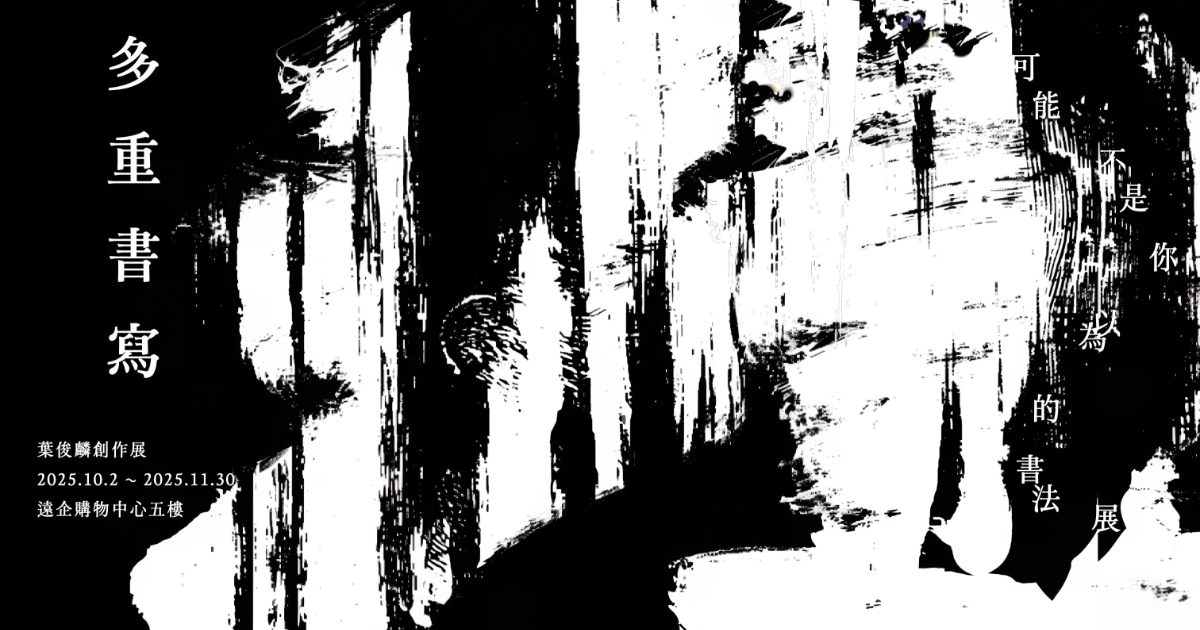
書法長久以來被視為展現個人美學與人格的藝術形式,講究基本功,要具備筆法、章法及書寫氣韻。然而隨著時代的推進,文字的使用情境與意義不斷轉變,當代書法該如何回應這樣的語境?這正是這次展覽企圖探索的問題。
「多重書寫」不僅意味著書寫上的多重可能外,更指向觀看的多重性。當書法不再僅作為文化象徵,書、寫、畫之間不再是穩定而單向,而是充滿不確定性時,是否能開啟另一種可能?也探討該如何在形式與內容之外,如何可以映照台灣當下的處境,展現無論是個人或社會,抑或科技帶來的挑戰與衝擊。
回望書法史,碑學運動曾因石碑拓本而開啟新的美學視野;而今日,數位字型是否正成為這個時代的「數位碑刻」?它們與我們的日常生活緊密相連,卻往往被忽視,而當數位科技與人工智慧逐漸滲入我們的日常經驗,書法該如何因應?而這些新的媒介,又能否為書寫開啟另一種未被想像的可能?
《多重書寫》邀請您一同探索與提問,在這個充滿矛盾與快速轉變的時代,書法究竟能以何種方式延續和存在?除了可以是人文書寫的延續外,或許也可以成為一面鏡子,折射我們所處的現實與未來,也希望藉由這次展覽,展開更多對話和探索各種可能。